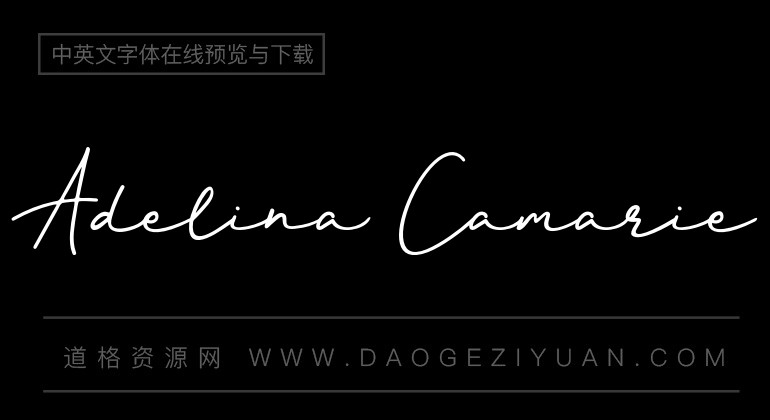
? Adelina Camarie 是一款由波兰设计师 Magdalena Frankowska 创作的字体,它具有精细、优雅的设计,适合用于印刷、网页和多媒体设计。Adelina Camarie字体的特点是其细节的处理,比如它的细节更加精致,字体的边缘更加圆润,使它看起来更加优雅,更加完美,同时它也具有良好的可读性和可访问性,可以满足多种设计要求。内容介绍
Adelina Camarie是一款非常不错的手写艺术字体,具有很好的视觉感,适合于文化类的宣传设计、商业类品牌的广告和产品包装设计以及个性化文字排版等较多场景。